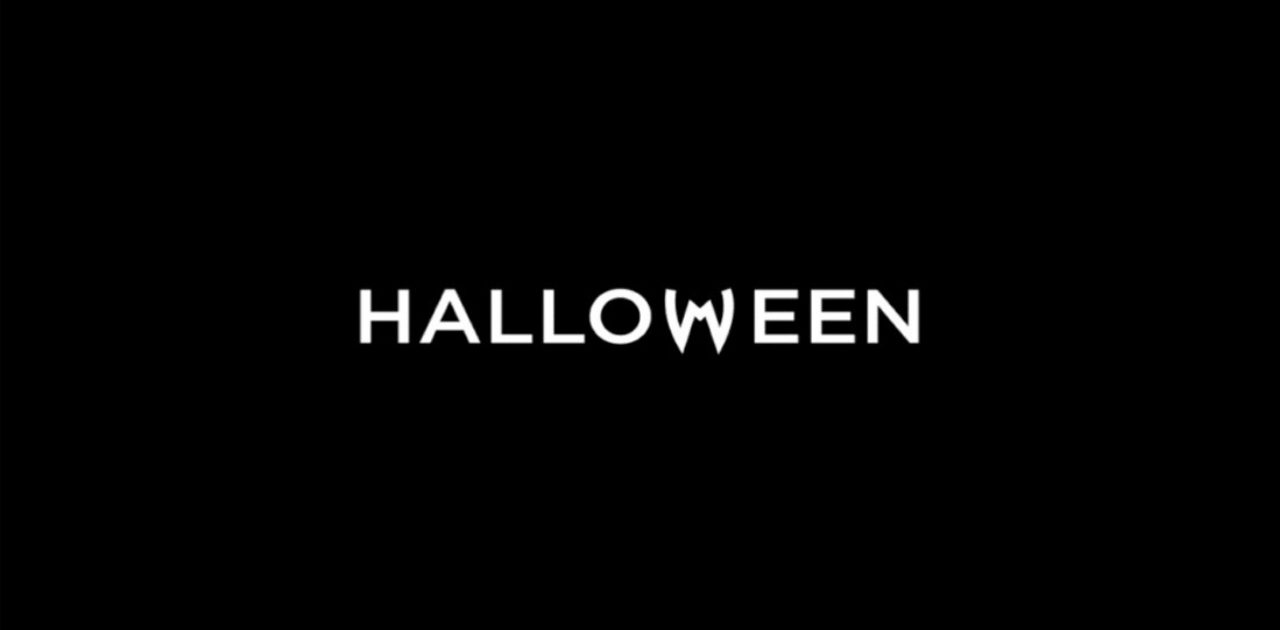
Designer cria tipografias animadas que representam o significado de suas palavras
Mindaugas Dudenas é um freelancer da Lituânia, conhecido por seus trabalhos minimalistas.
Ele criou o projeto Type in Motion, uma série de logotipos que explora os significados por trás das palavras com animações muito inteligentes.
1. Gostar
2. Vento
3. Verão
4. Siga-me
5. Volume
6. Sorrir
7. Chorar
8. Halloween
9. Gravação
10. Portas
11. Interruptor
12. Ginástica
13. Tick-Tack
14. Tempo
15. Xadrez